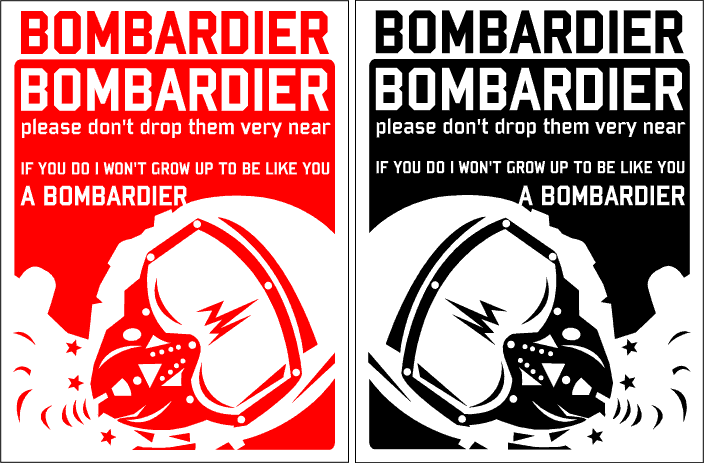
Suche blockige Schrift mit abgeschrägten Ecken (Beispielbild anbei)
ich bin auf der Suche nach blockigen Schriften mit abgeschrägten Ecken.
Ähnlich wie die auf dem Beispielbild.
Hat da jemand ein paar Tipps auf Lager?